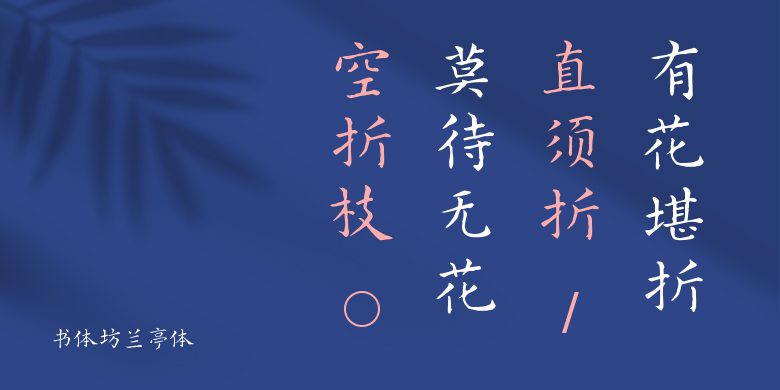
书体坊兰亭体
书体坊兰亭体,这款字体结构工整、笔画清晰,兼顾美观与易读性,适用于标题、正文、海报、包装、LOGO 等多种场景。字形优雅稳定,风格百搭耐看,适配日常排版与创意设计,让文字呈现更舒适、更具质感。书体坊兰亭体一笔一画,皆是细节,以均衡的比例、流畅的线条打造舒适视觉体验,字形端正大气,风格简约现代。无论是商业设计、品牌宣传还是日常排版,都能轻松驾驭,让文字更有格调与力量。书体坊兰亭体字体下载。